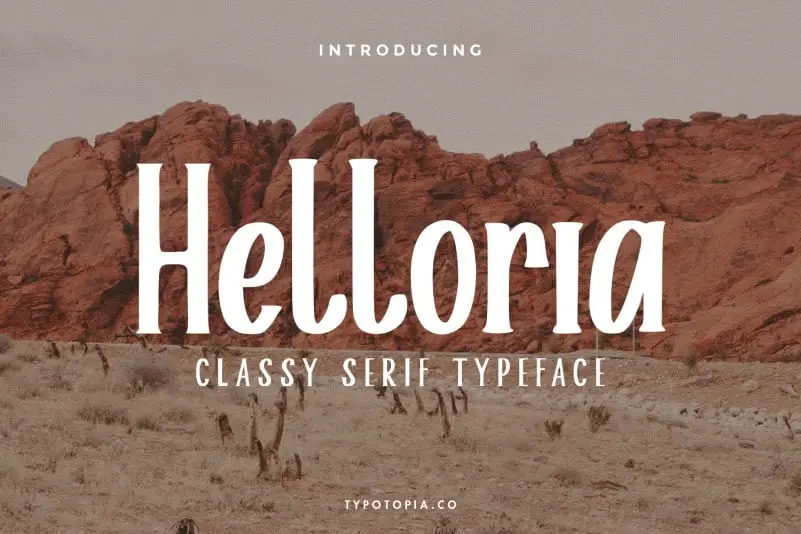
Helloria Classy Serif Font – Download Grátis
A Helloria Classy Serif é uma fonte exótica e interessante para a categoria Display Fonts criada pela typotopia. Essa fonte surge com uma personalidade única, sendo perfeitamente adaptável para um vasto conjunto de projetos gráficos desde logomarcas até cartões degradados e embalagens de produtos. Ela se destaca como uma escolha ótima para elementos visuais criativos, tais como assinaturas de produtos ou cartazes em grandes dimensões. Suas linhas elegantes e detalhes sofisticados a tornam perfeita não apenas para uso impresso em cartões de convite ou etiquetas, mas também para ambientes digitais, como logotipos ou letras da carta que adicionem um toque de sofisticação a qualquer projeto. A Helloria Classy Serif é uma fonte versátil e singular ideal para quem busca incorporar detalhes criativos em seu próximo design.